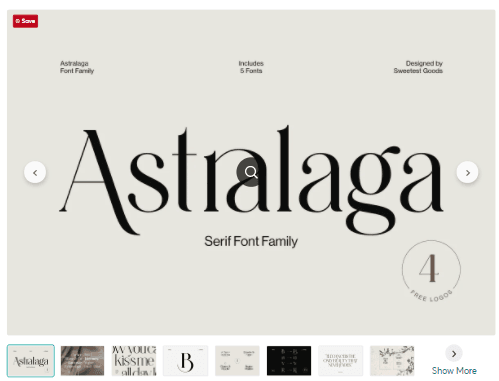
Astralaga - Elegant Font Family
Элегантный, изящный и неподвластный времени. Astralaga - это универсальное семейство шрифтов с вневременной классической привлекательностью, более 50 альтернативных вариантов и лигатур, многоязычной поддержки и 4 лучших бесплатных дизайна логотипов. (И мы думаем, что это пока наша лучшая работа! )